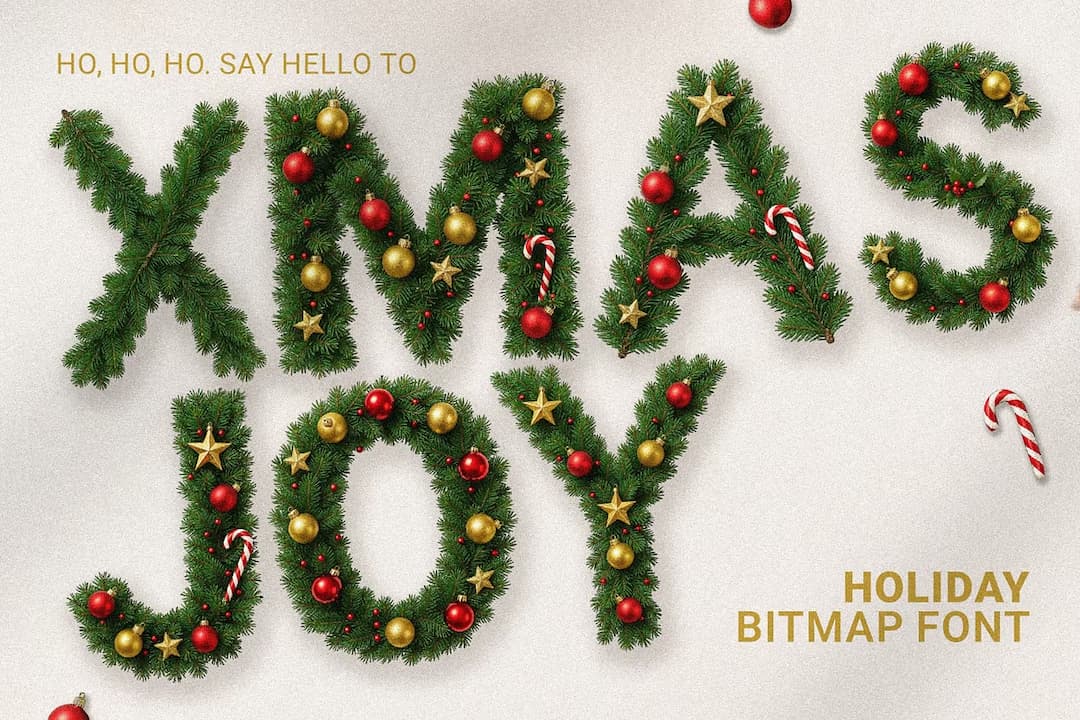
意識を失っていたかと思うほどもう12月なので(日本語?)こちらを紹介。これぞ年末というようなクリスマスツリーを模した書体。モミの木の枝で形成されたグリフに、オーナメントがごたっと付いたフォントである。これは OpenType のカラーフォント機能を使っており、Adobe Illustrator などの対応アプリを使えばこのように色が付いた文字がそのまま出てくるという便利なヤツである。今どきかなり珍しい「ビットマップフォント」とあるので、拡大すると荒れてしまう事が懸念されるが、これだけ細かく色分けされてるとまあしょうがないという感じである。小文字グリフにはオーナメントなしが割り当てられてるようだが、まあ使わないよね(笑)。